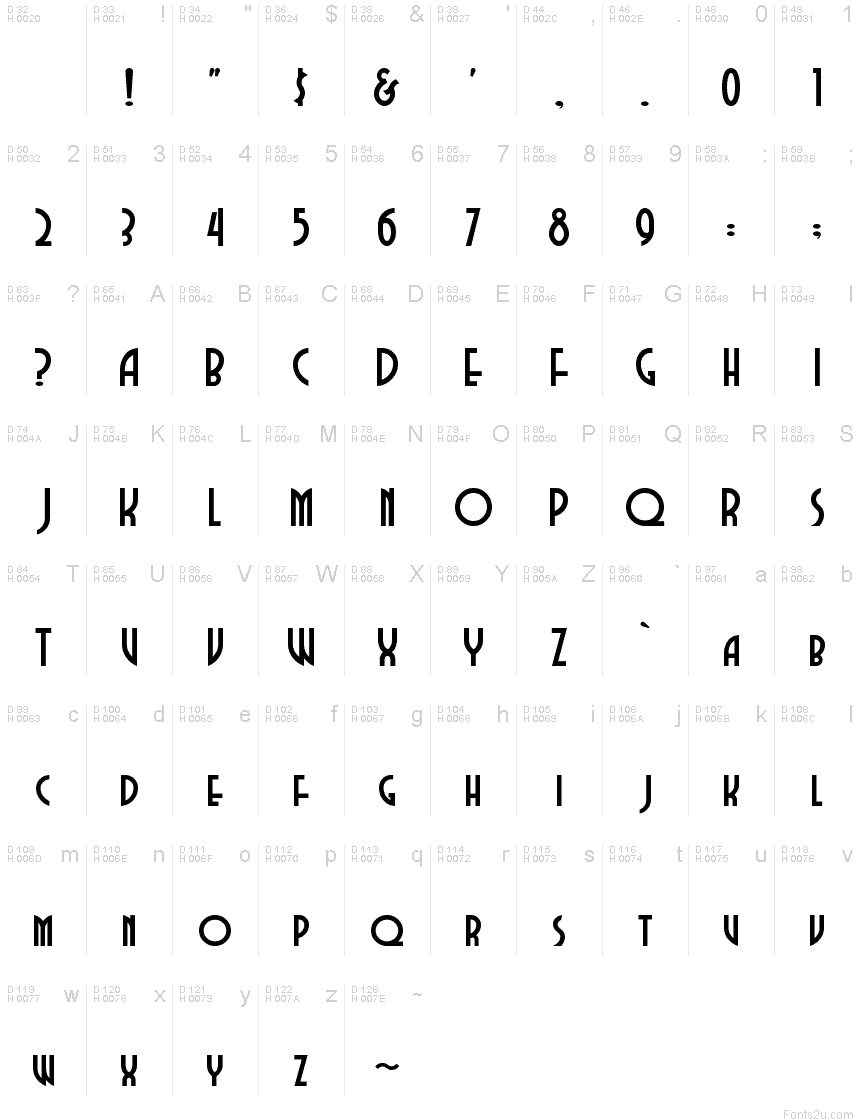
يُعد DubbaDubbaA من Nick Curtis خطاً مجانياً بنمط ريترو (Retro Display) يتميز بحروف طويلة ومضغوطة ذات خطوط سميكة ومشبّعة تكاد تتداخل مع بعضها. تمنحه الخطوط العمودية الدرامية والمنحنيات الداخلية المجوفة مظهراً جريئاً وجاهزاً للملصقات، حيث يجمع بين طابع لوحات الإعلانات في صالات الستينيات وتصميم أغطية الأسطوانات القديمة. إنه خط مؤثر ودرامي، صُمم ليبرز بقوة في العناوين الكبيرة.
مع استخدام DubbaDubbaA، ستجذب عناوينك الانتباه فوراً على ملصقات الفعاليات، ومنشورات النوادي، وأغلفة الألبومات، والشعارات، وتغليف المنتجات، وتصاميم السوشيال ميديا. يتألق هذا الخط المجاني عند استخدامه بحجم كبير مع القليل من التباعد الإضافي ليسمح لأشكاله الضخمة بالتنفس. قم بإقرانه مع خط بلا زوائد (Sans Serif) هندسي ونظيف في النصوص الصغيرة للحفاظ على القراءة الواضحة، بينما يتولى DubbaDubbaA مهمة السرد البصري الجريء بطابعه الريترو.